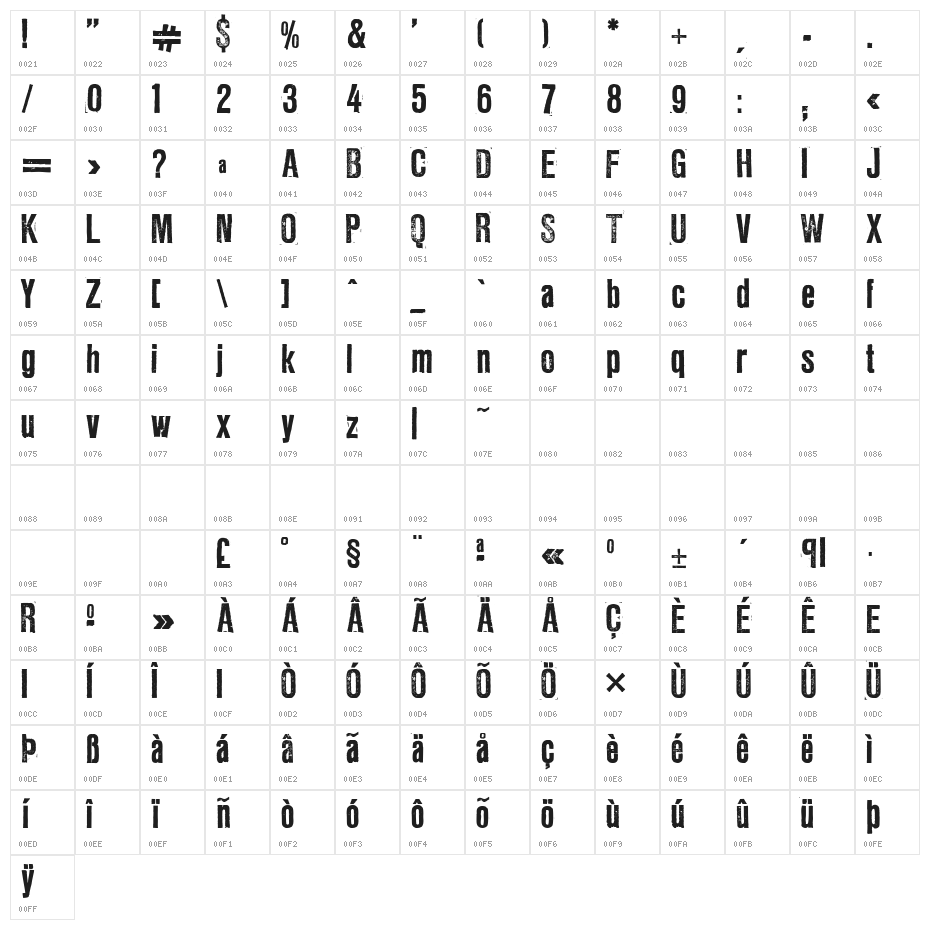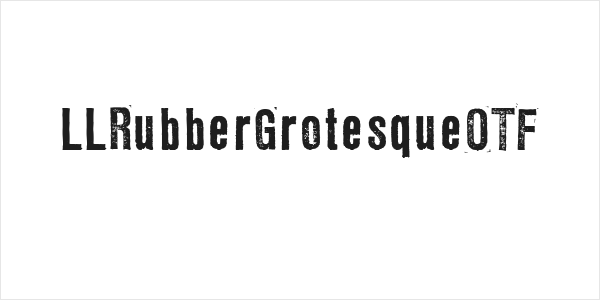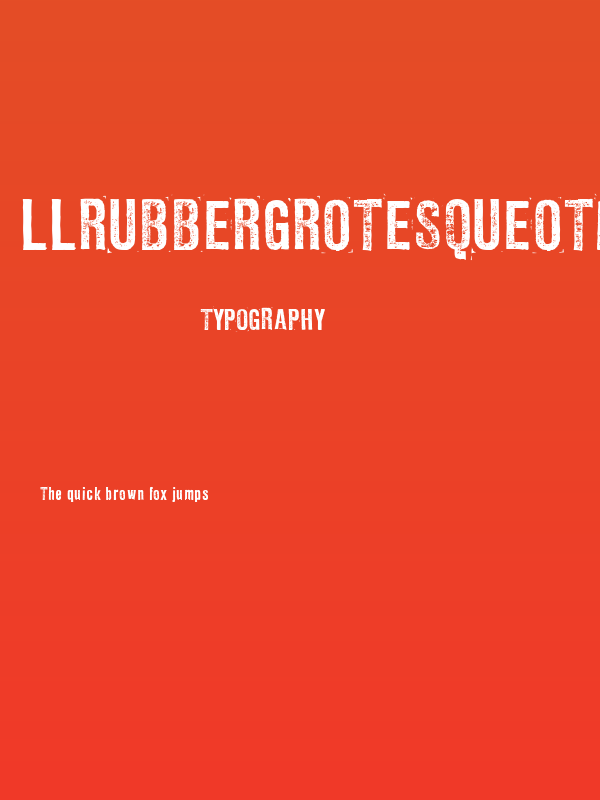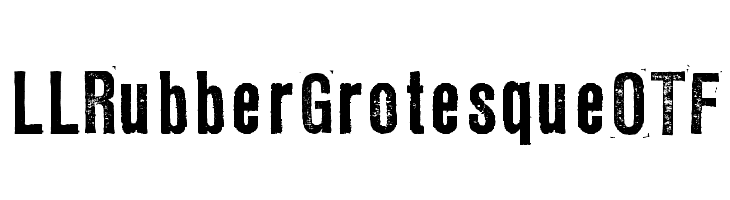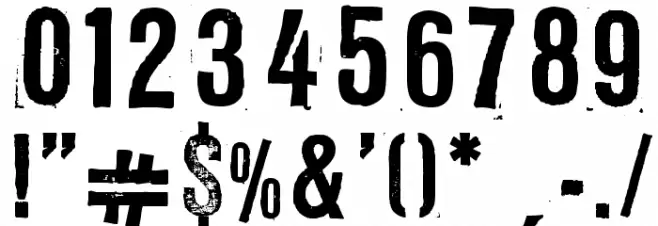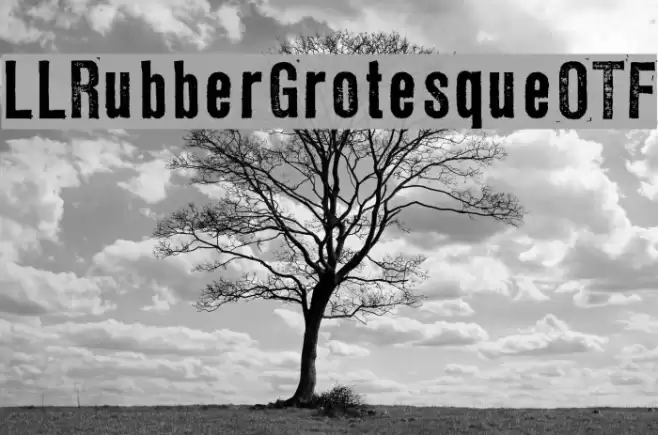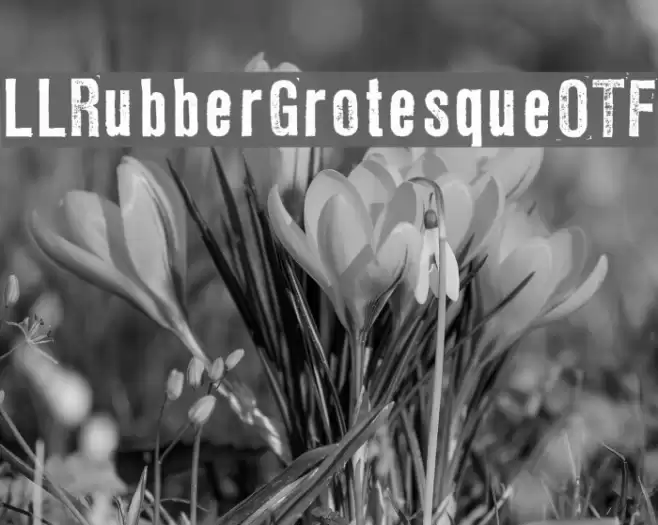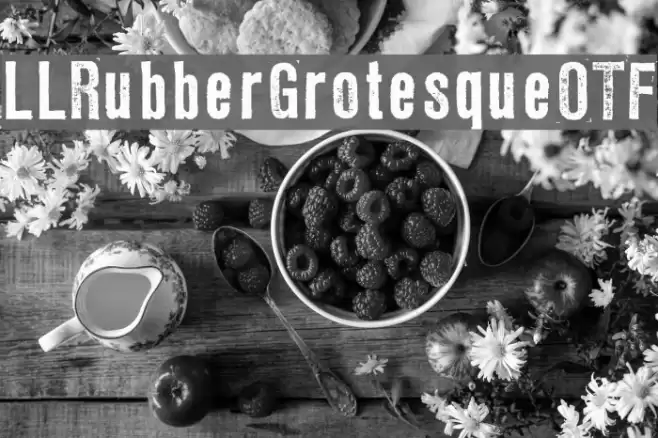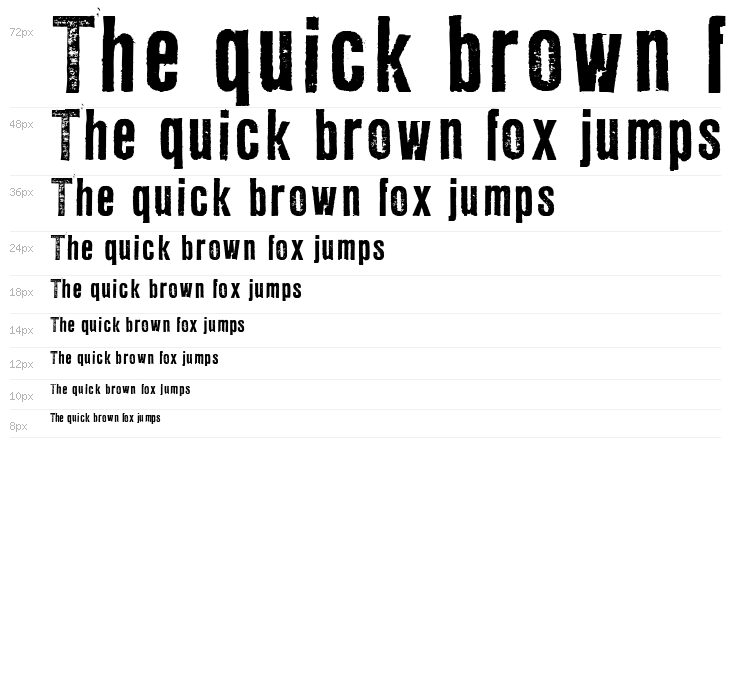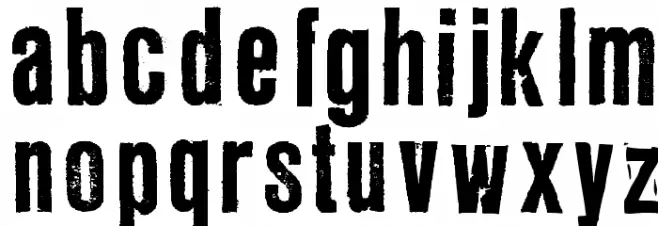
LLRubberGrotesqueOTF Font
✎ Distorted Eroded
| Categorías | Distorted Eroded |
| Estilo general | Vintage |
| Proyectos propuestos | Ideal for vintage posters, album covers, branding for rustic or industrial-themed businesses, and any design needing a bold, gritty aesthetic. |